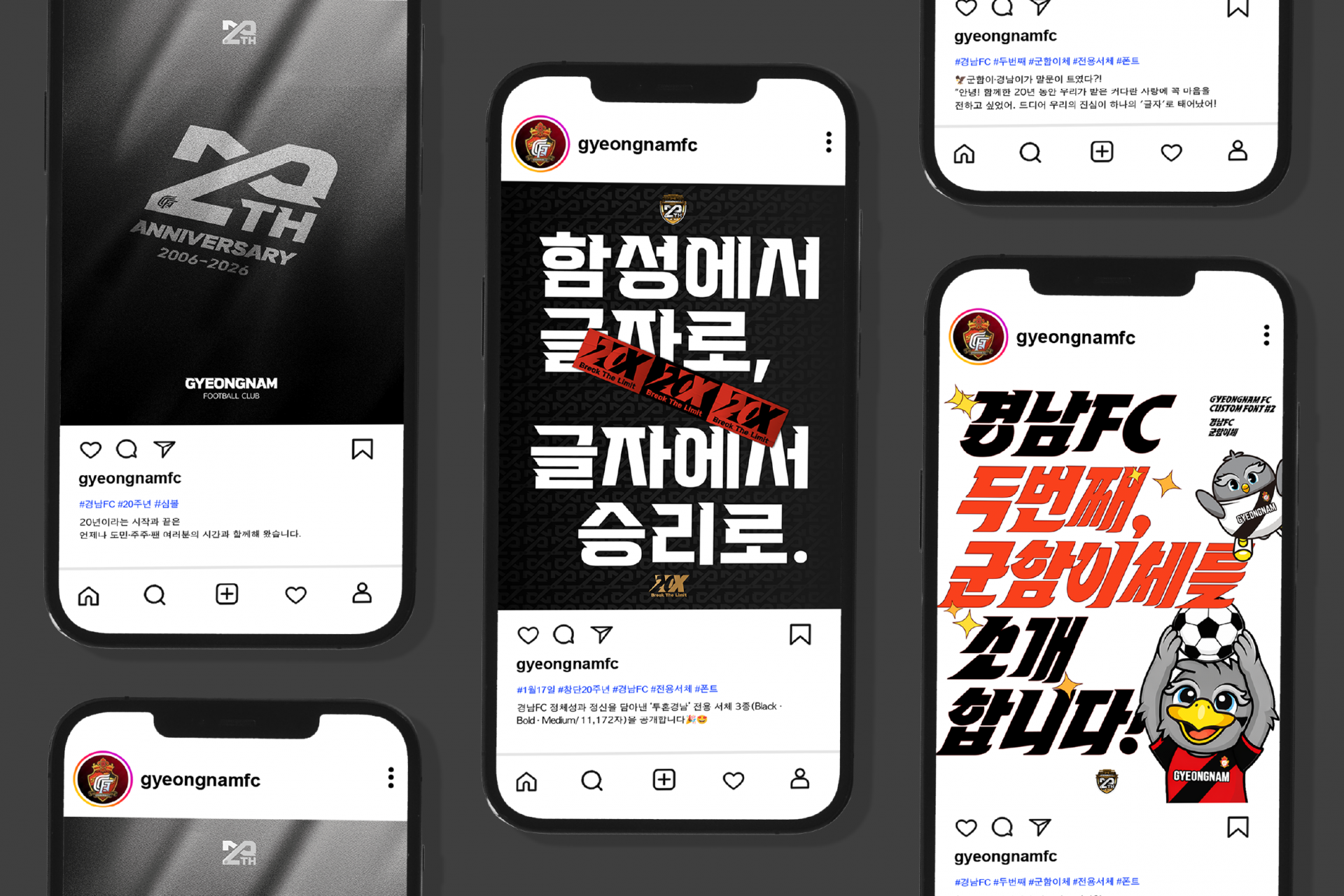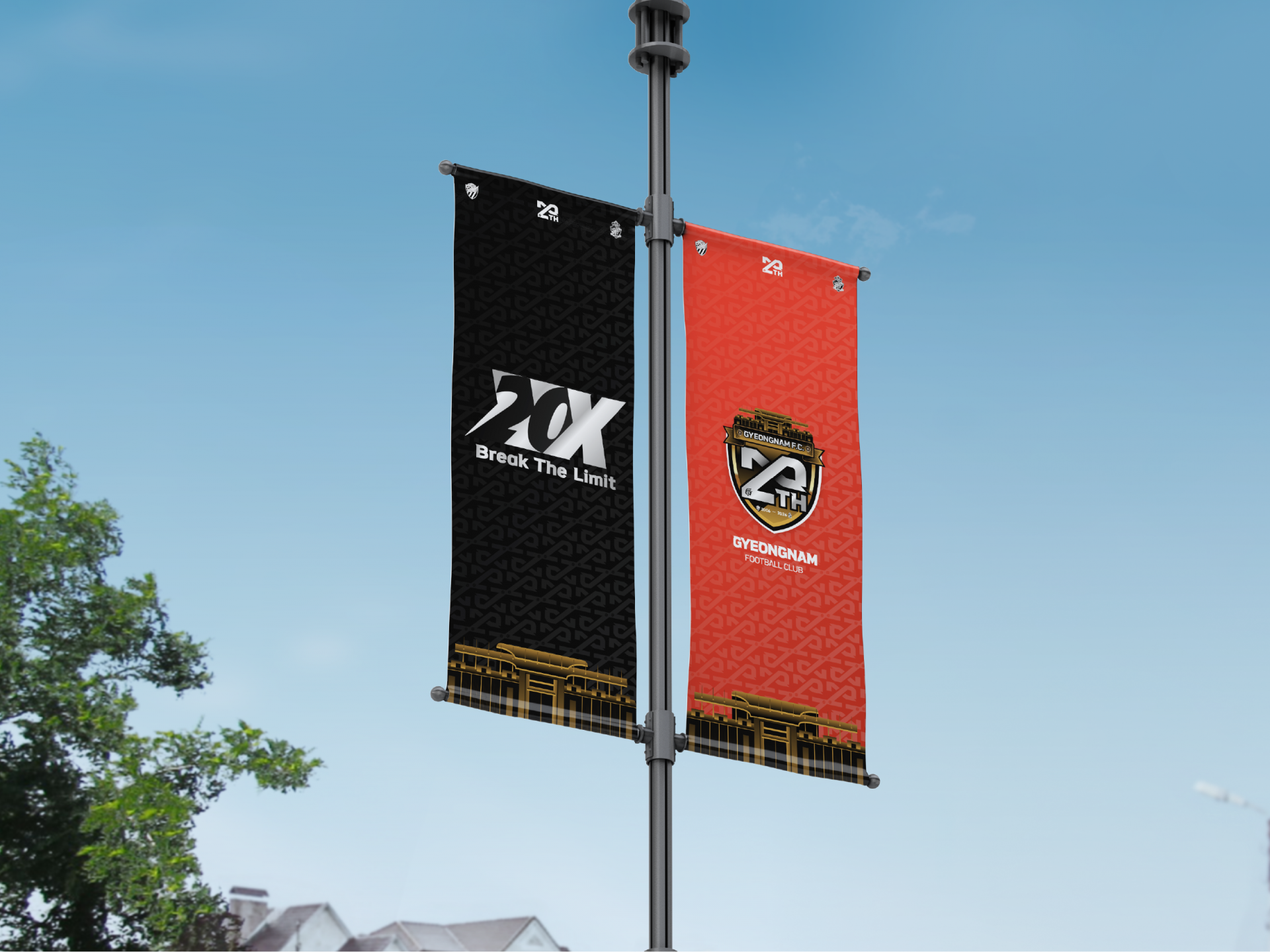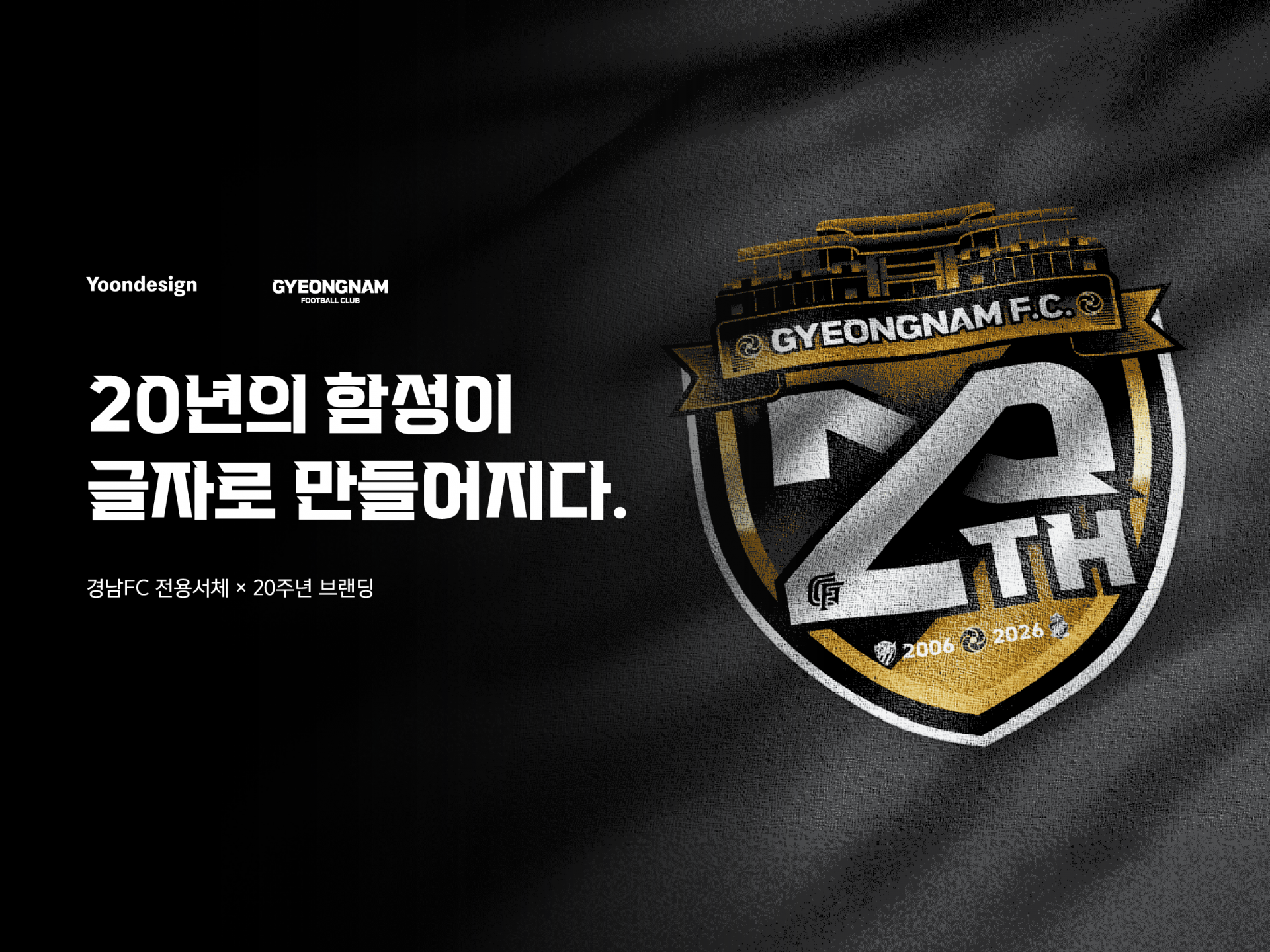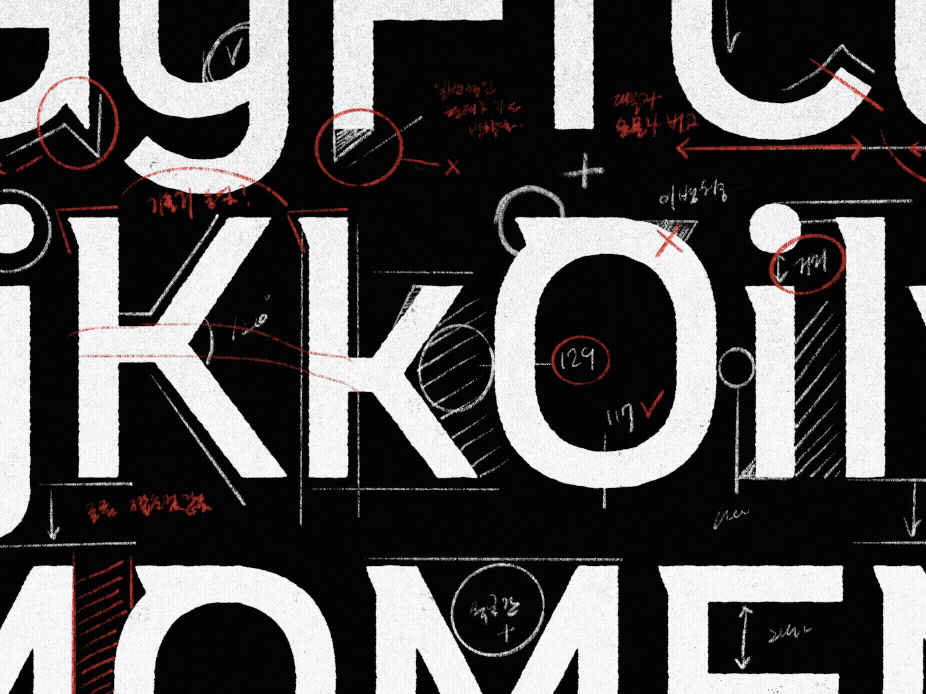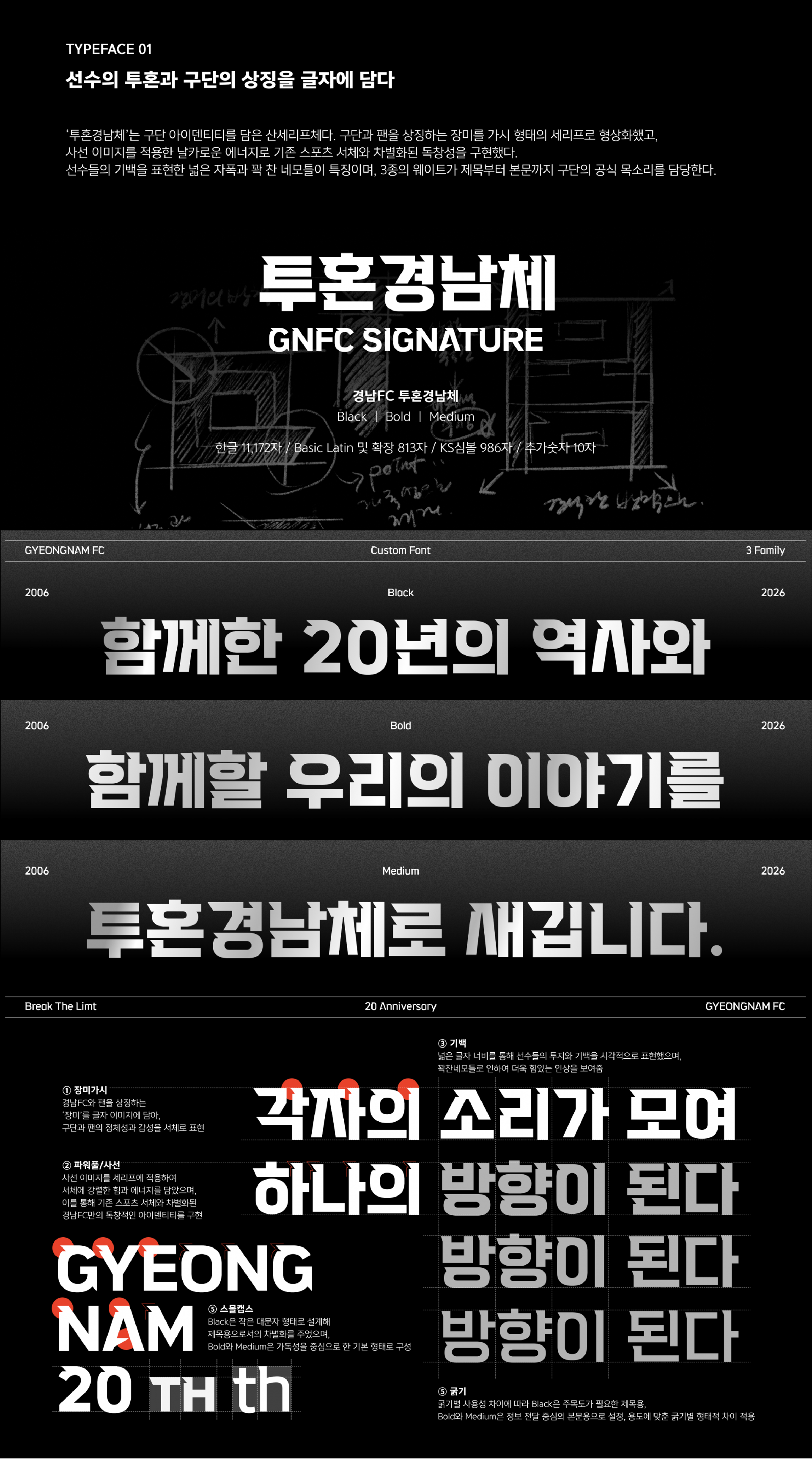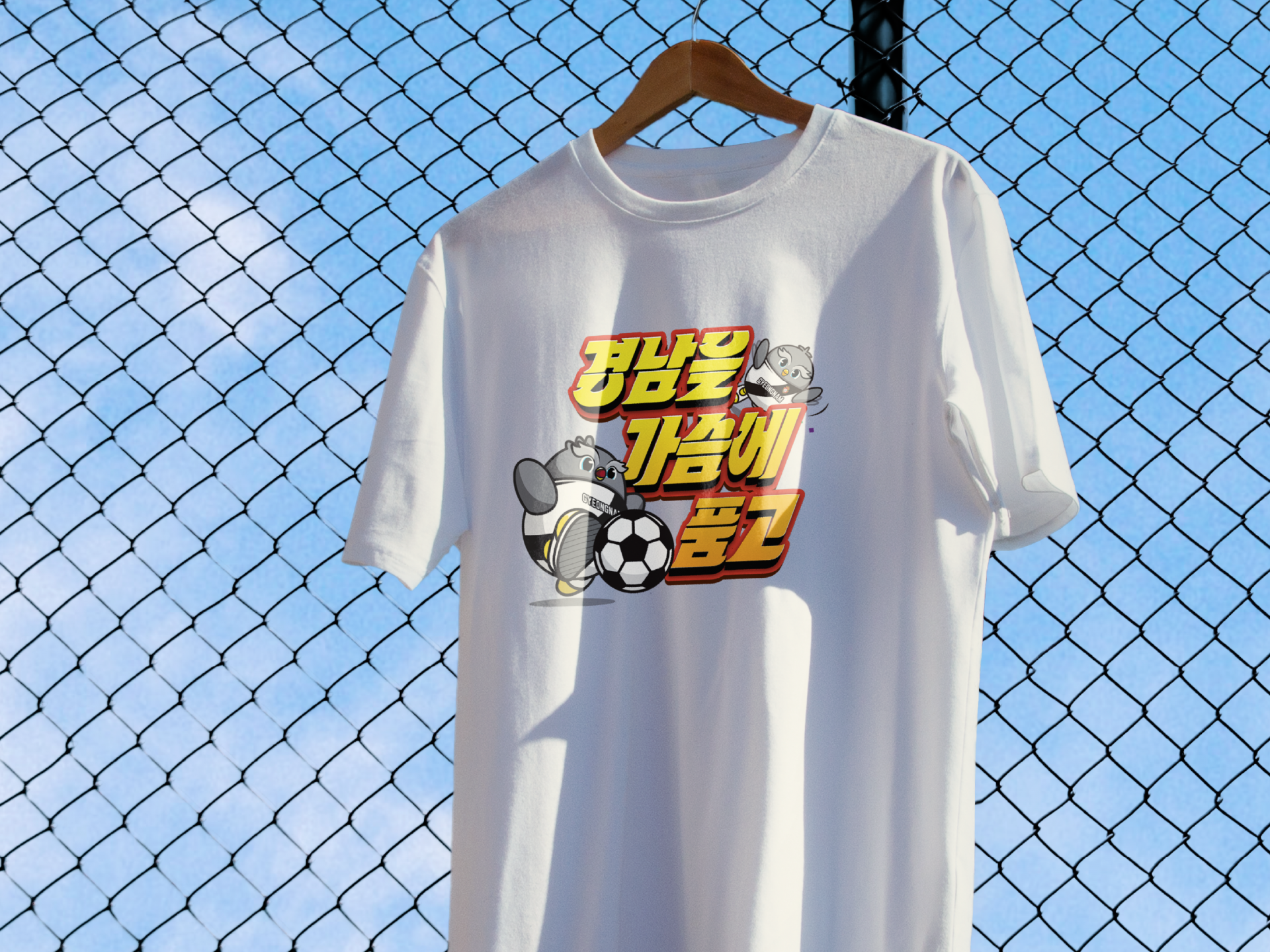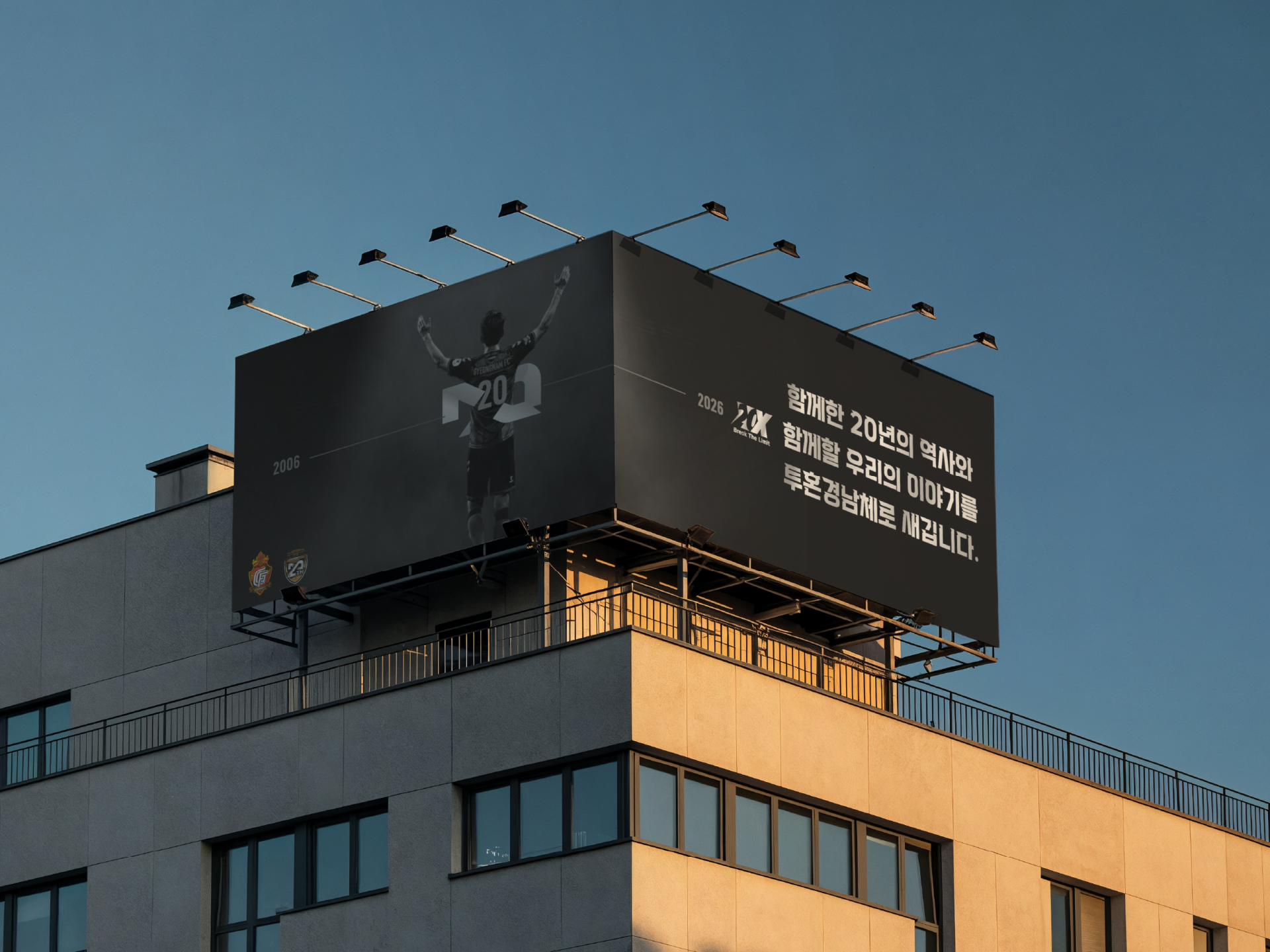
경남FC [투혼경남체, 군함이말문트였체]
경남FC 창립 20주년 기념으로 폰트 [투혼경남체]와 [군함이말문트였체]를 개발하였다. [투혼경남체]는 장미의 가시 같은 세리프, 사선을 모티프로하는 획과 단단한 골격으로 경남FC의 투혼과 정체성을 시각화하였다. 꽉 찬 모듈 설계는 단단한 무게중심으로 '투혼'의 정신을 담고 있다. [군함이말문트였체]는 경남FC의 마스코트 '군함이'와 '경남이'를 모티프로하여, 과감한 기울기와 군함조를 연상캐하는 날카롭고 속도감있는 인상을 담아 독창적이고 개성있는 외형으로 디자인했다.
경남FC [투혼경남체, 군함이말문트였체]